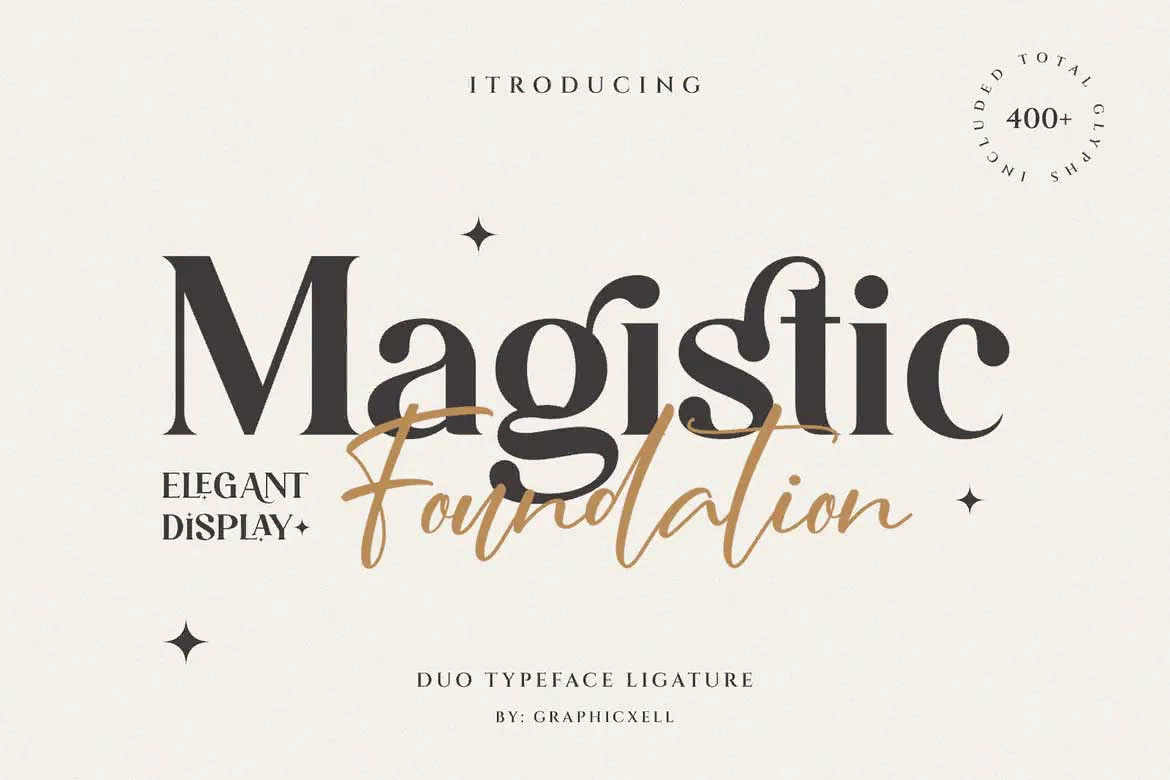
Название: Magistic Foundation Font (2021)
Magistic Foundation - это крутой, смелый и универсальный шрифт в дуэте (шрифт и засечка).
Он характеризуется плавными изгибами и идеально подходит для модного брендинга или редакционного дизайна.
Смело добавляйте его в свои проекты, и вы будете в восторге от результатов.
Название: Magistic Foundation Font (2021)
Magistic Foundation - это крутой, смелый и универсальный шрифт в дуэте (шрифт и засечка).
Он характеризуется плавными изгибами и идеально подходит для модного брендинга или редакционного дизайна.
Смело добавляйте его в свои проекты, и вы будете в восторге от результатов.